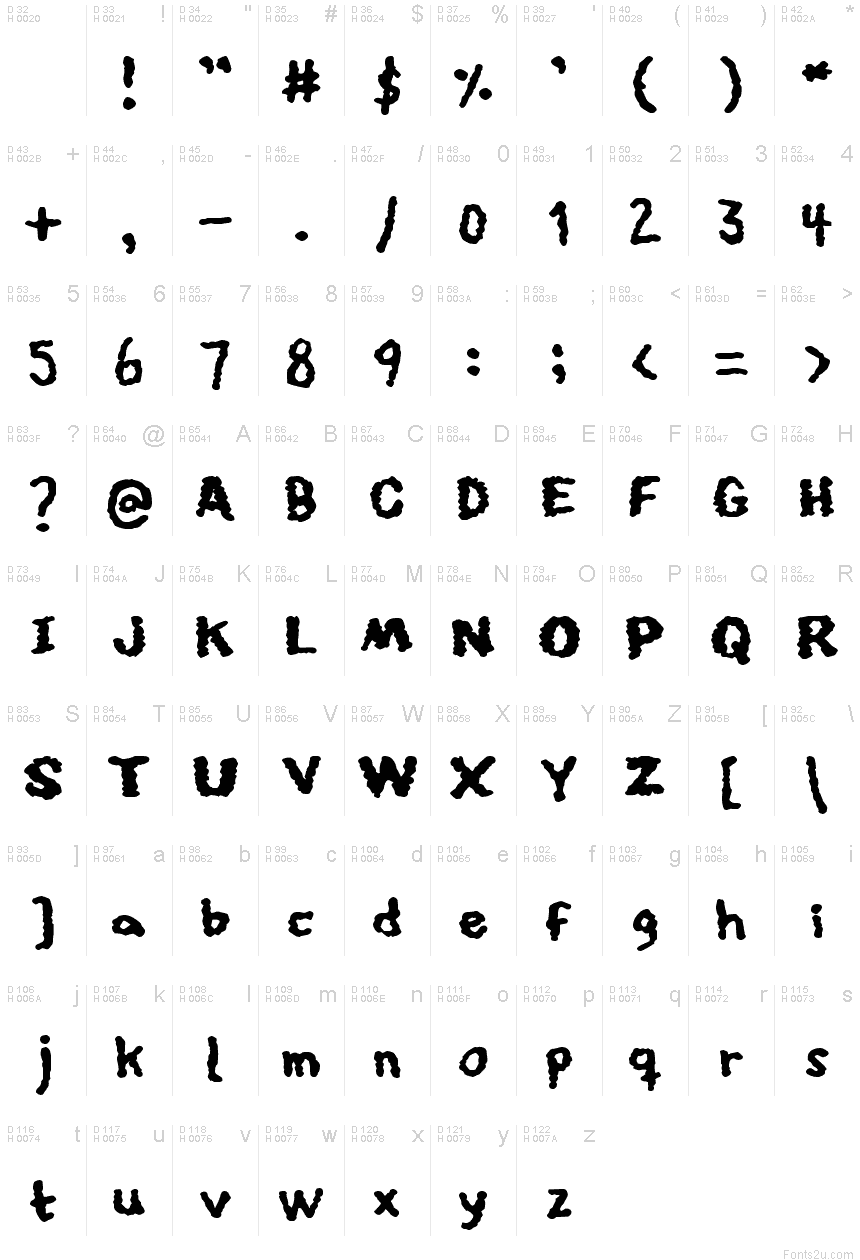
خط Youthquake من تصميم Jakob Fischer هو خط عرض (Display) مجاني ذو طابع متآكل ومظهر مقصوص يدوياً، يجمع بين روح منشورات البانك وتأثير الكتابة بقلم الماركر الملطخ. الحروف ضخمة وغير منتظمة، مع حواف مهتزة ووصلات متورمة تمنح الخط طابعاً صاخباً وخاماً ومتمرداً قليلاً.
يناسب هذا الخط الملصقات، وأغلفة المجلات المستقلة (Zines)، وتصاميم موسيقى "الإندي"، ورسومات فعاليات الهالوين، والعناوين القصيرة على العبوات حيث يمكن لتلك الصورة الظلية المهترئة أن تعبر عن نفسها بوضوح. وبما أنه خط مجاني، فإن Youthquake يعد خياراً ممتازاً لبطاقات العناوين، وتصاميم الملصقات، واسكتشات الشعارات السريعة، خاصة عندما تبحث عن حروف خام وعضوية بعيداً عن التصاميم المصقولة أو المرتبة.